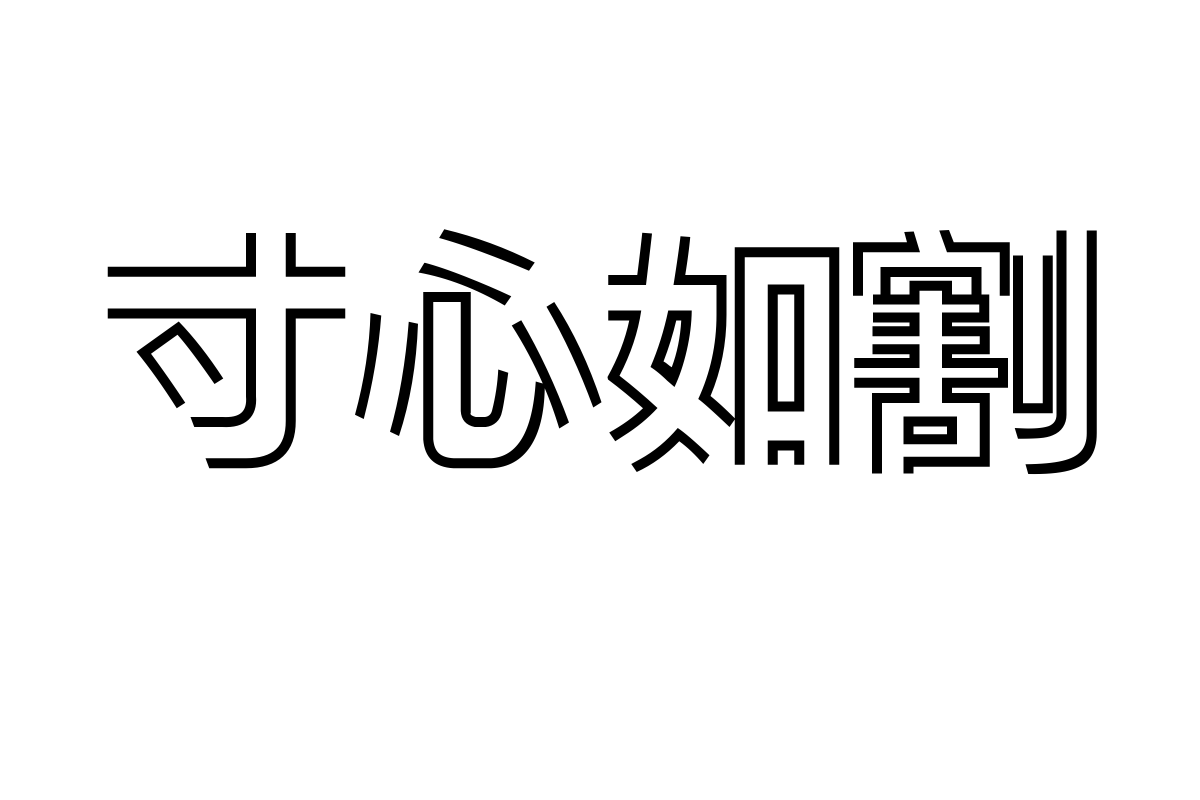
锐字真言中国清零体-闪(REEJI-CHNWakeupGB-Flash)是一款专为中文环境设计的字体,具有独特的风格和特点。该字体采用了现代设计手法,将中国传统书法与现代平面设计相结合,创造出一种新颖、独特的视觉体验。
锐字真言中国清零体-闪的字体特点:
1. 字形独特:该字体采用现代设计手法,将中国传统书法与现代平面设计相结合,创造出一种新颖、独特的视觉体验。
2. 字体风格:锐字真言中国清零体-闪的字体风格简洁明快,线条流畅,给人一种轻松愉悦的感觉。
总之,锐字真言中国清零体-闪是一款具有独特风格和特点的字体,适合用于各种需要展示中文环境的场合。